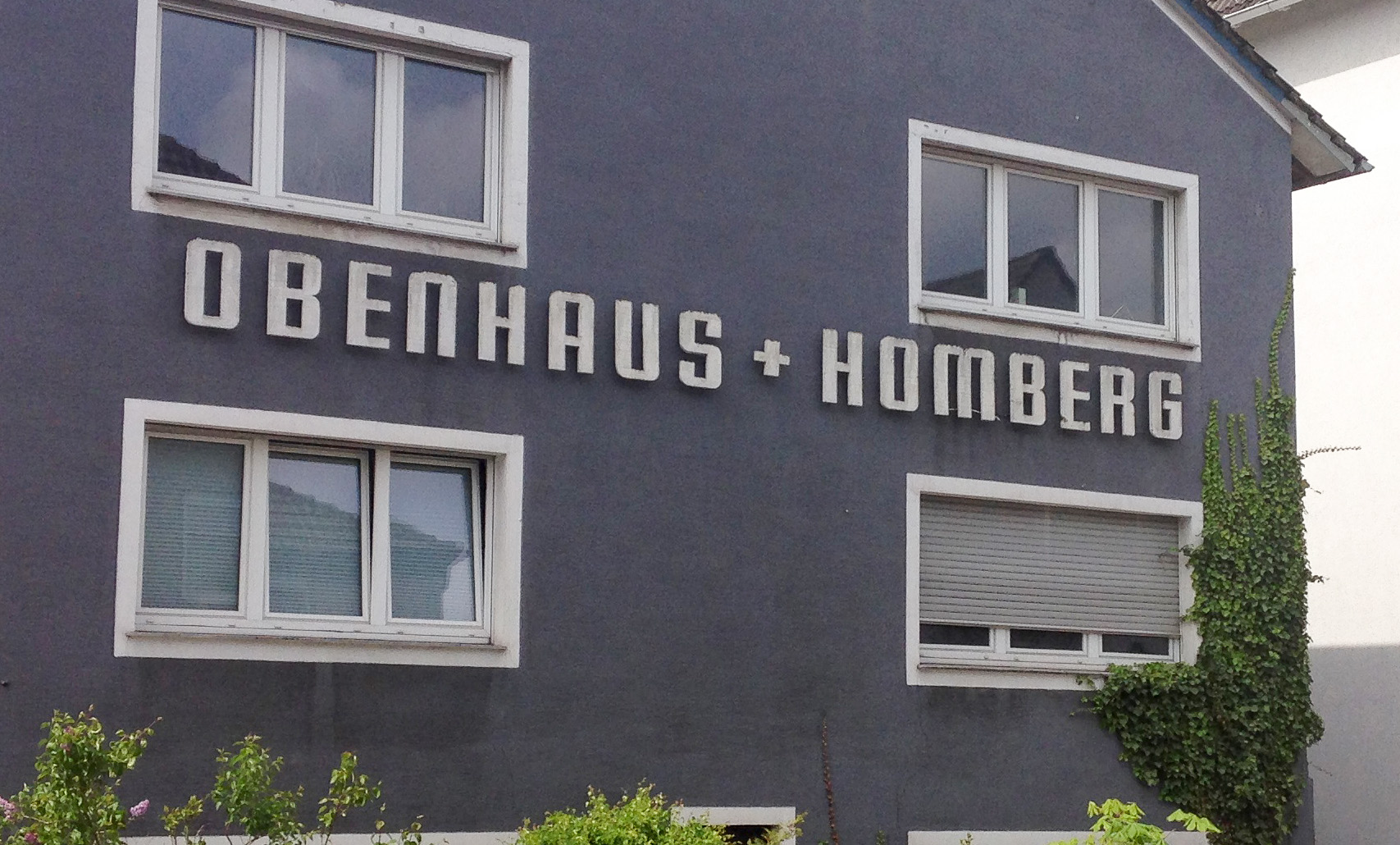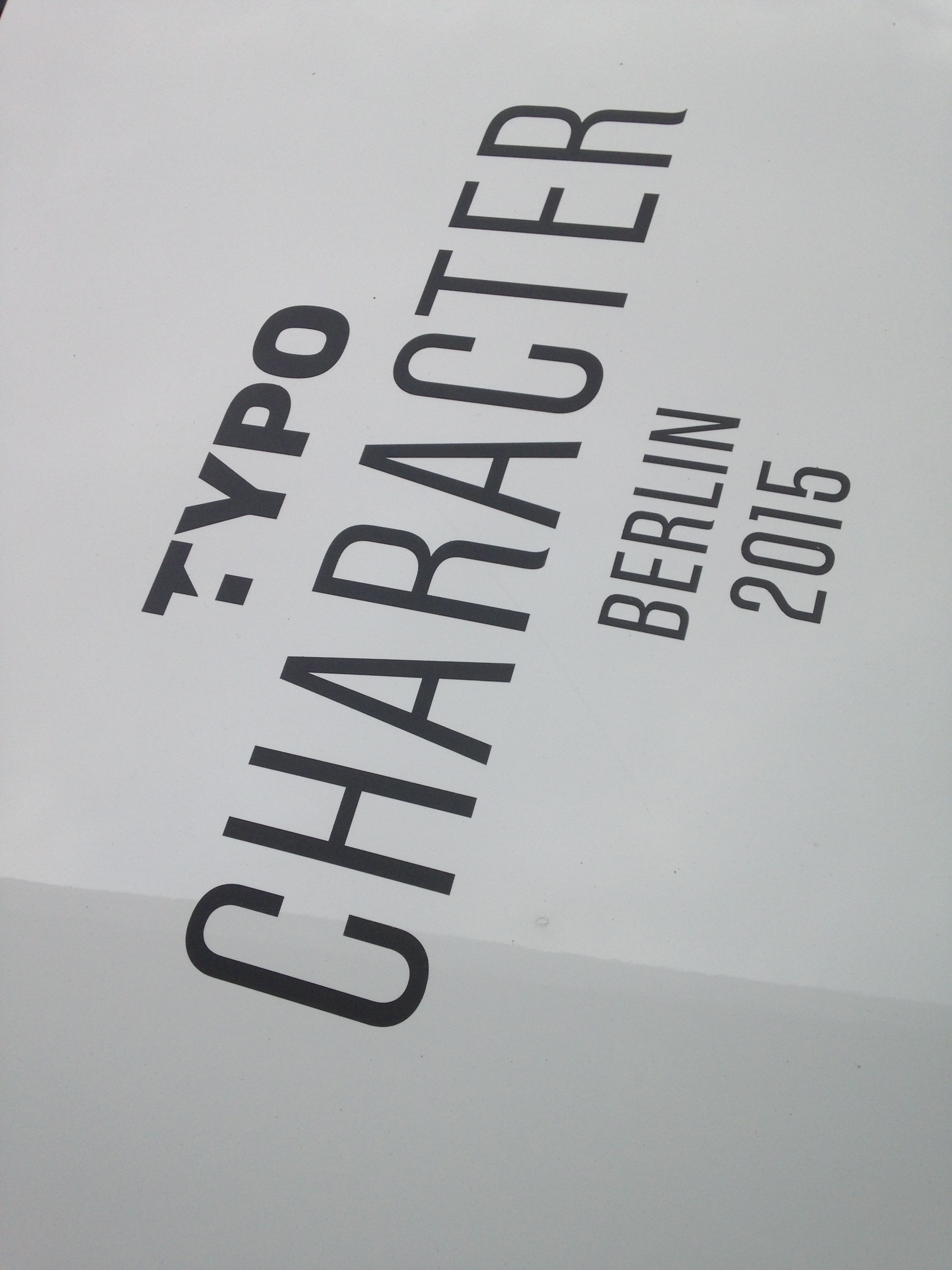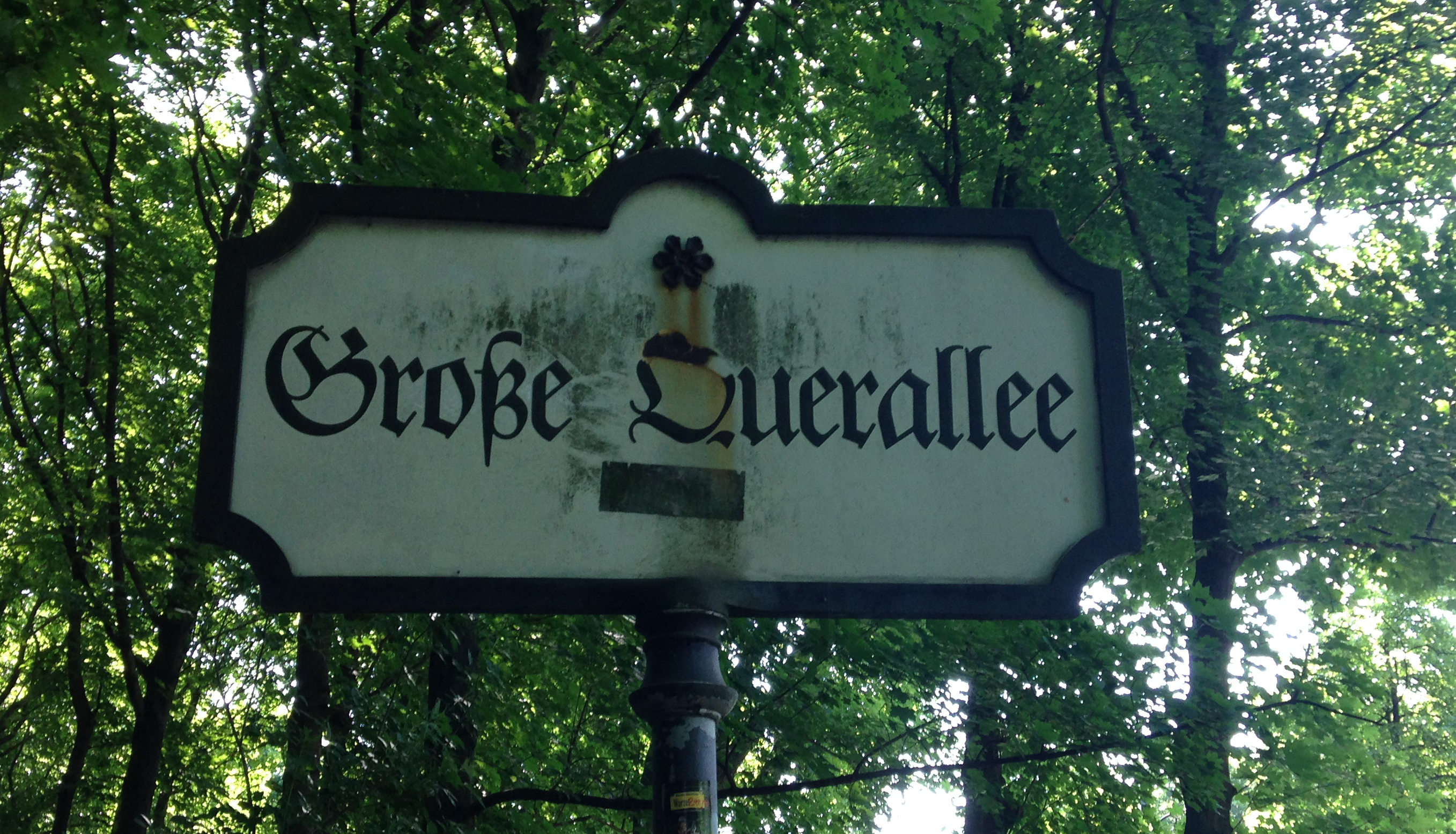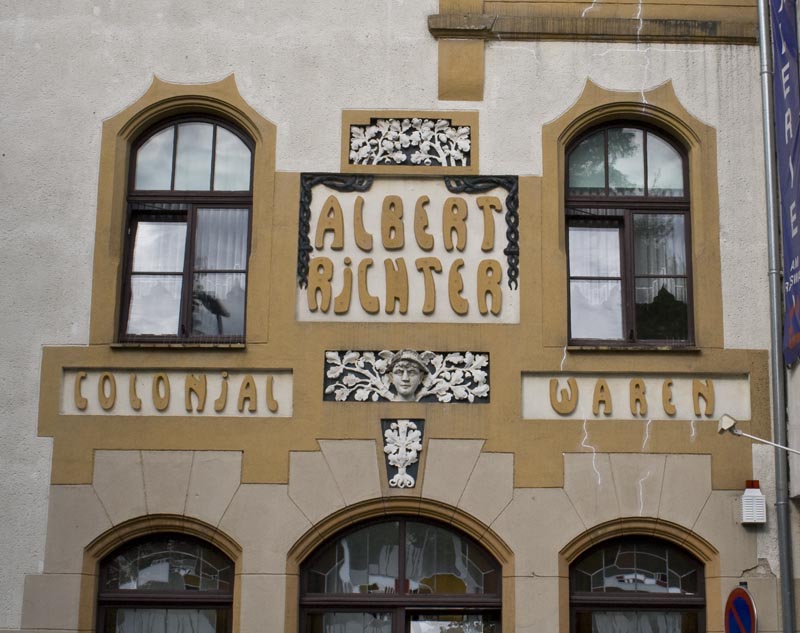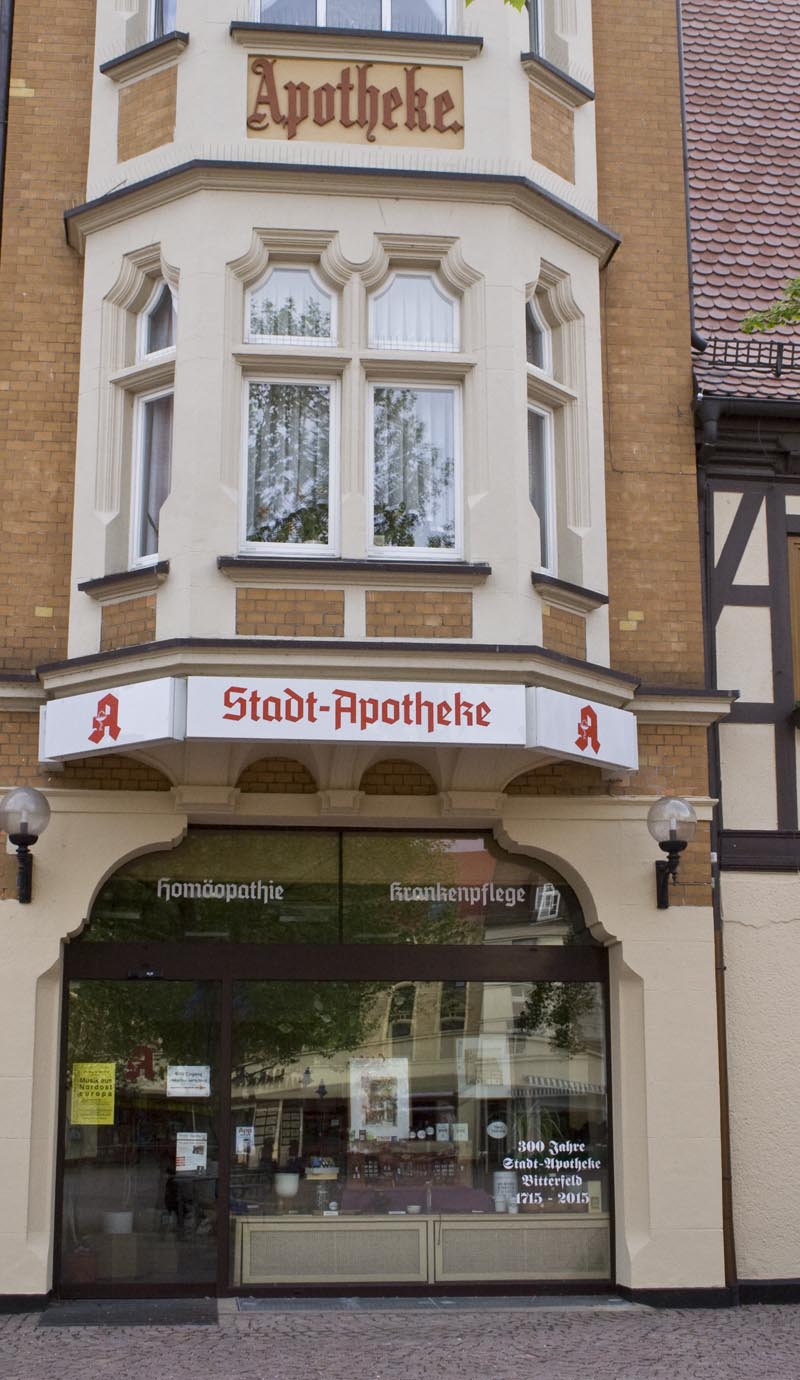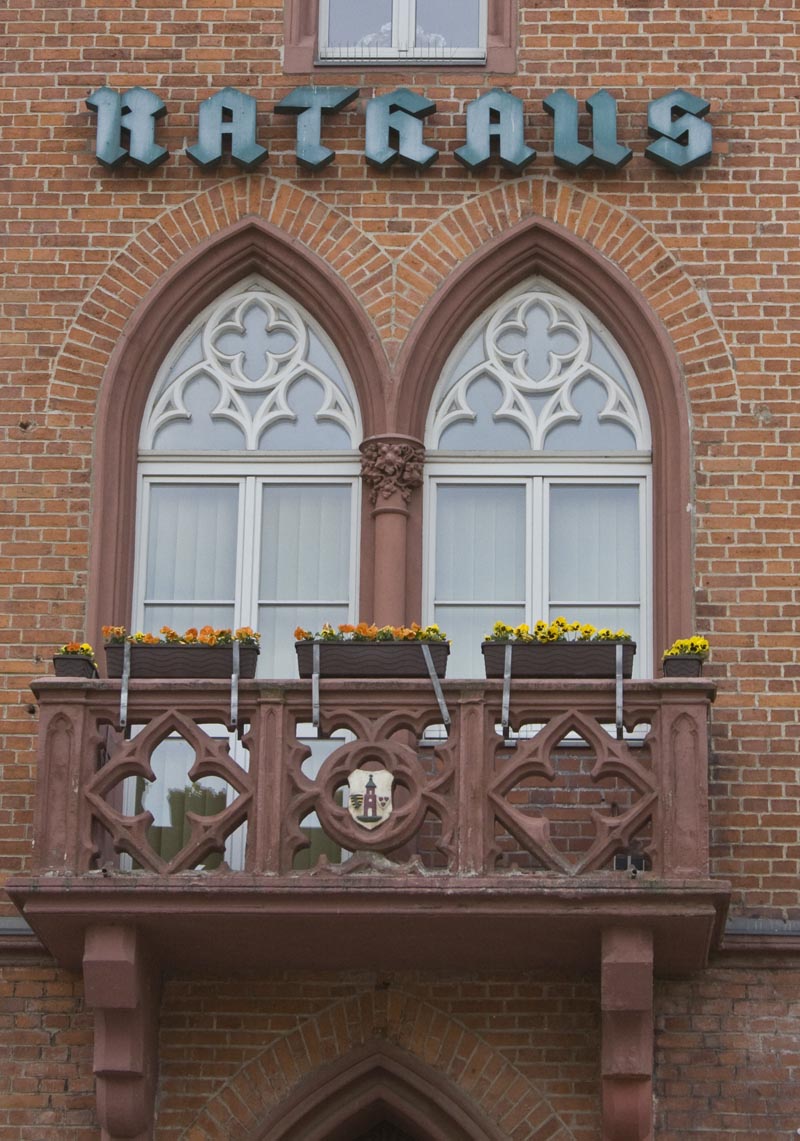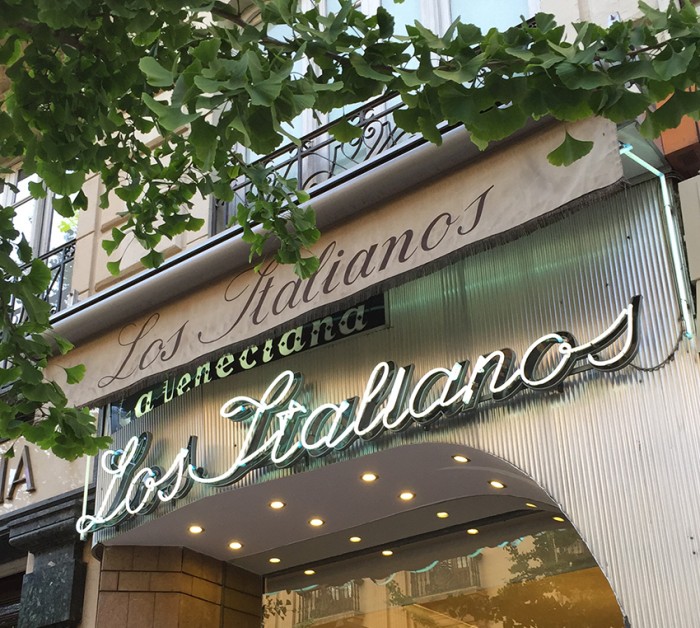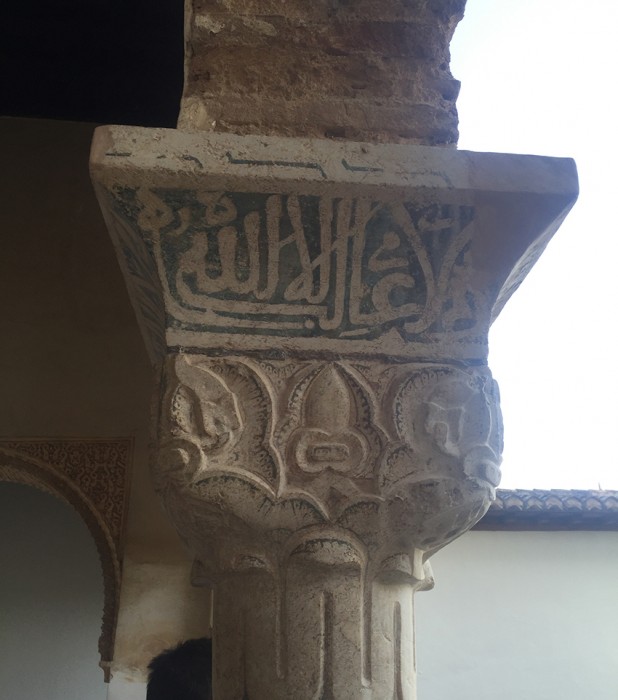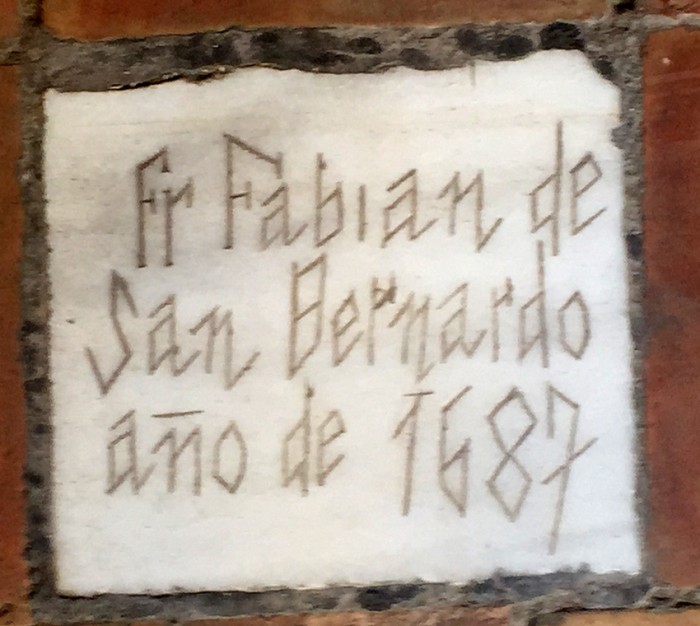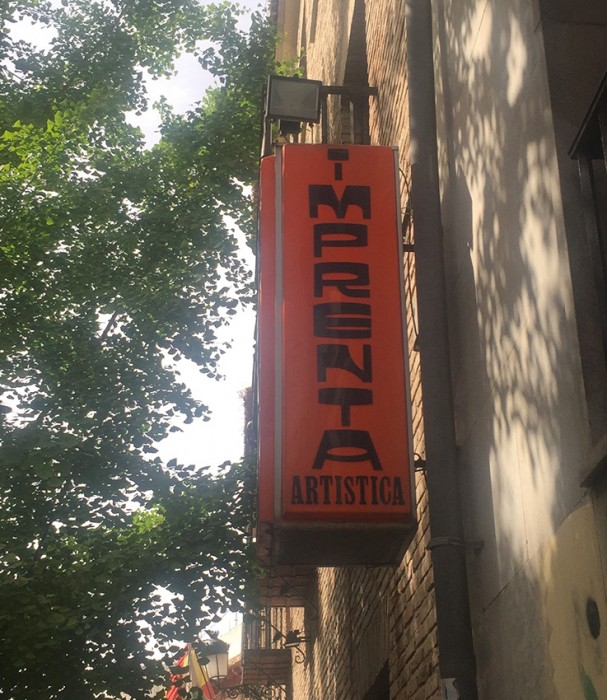
Typostreifzug durch die Stadt ...
das evangelische g ist ziemlich kuhl
Das obere ist aber eindeutig lebendiger – das darunter sieht schon ein klein wenig müde aus.  ;-)
Steinhude, Niedersachsen
Bitterfeld:
Apothekerin: Wir haben da so eine alte Schrift am Haus, da müßten Sie bei der Ladenbeschriftung aber Bezug drauf nehmen.
Provinzwerbefuzzi: Ja klar, mach ich, so was hab ich auch.
………
Jahre später:
Apothekerin: Aber für die Jubiläumsbeschriftung hätte ich dann doch gern ein paar mehr Schnörkel. Noch mehr so wie die Schrift am Haus.
Provinzwerbefuzzi: Ja klar, alt und Schnörkel kann ich auch.
Aber das ist doch der Hammer:
Na, wer ist der erste, der einen Font draus bastelt?
Die letzte Schrift sieht ein bisschen aus, als hätte man Lakritzschnecken abgerollt und Schrift daraus gelegt.
Hab ich auch nicht so gesehen, mein erster Gedanke war auch: "Au weia, ist die schräg, wer erfindet den so was?", wobei z.B. das z wirklich recht gewagt ist.
Vielleicht war es der Firmeninhaber selber, der da zum Stift gegriffen hat? Das gab es ja früher™ häufiger.
Na, wer ist der erste, der einen Font draus bastelt?
Erübrigt sich die Frage in diesem Forum nicht? :huhu:
Gut gemeint! – Kopfwehschaufenster in Zürich
Och mönsch, wie schade  :-(
Da hätte man sowas schönes draus machen können ...
an der Kathedrale gab es alte Graffitis in ca 4m Höhe, über die ich leider bisher keine weiteren Infos finden konnte.
Grabplatte in einer Kirche …
… und aus dem Kreuzgang eines Klosters. (sorry für die Unschärfe)